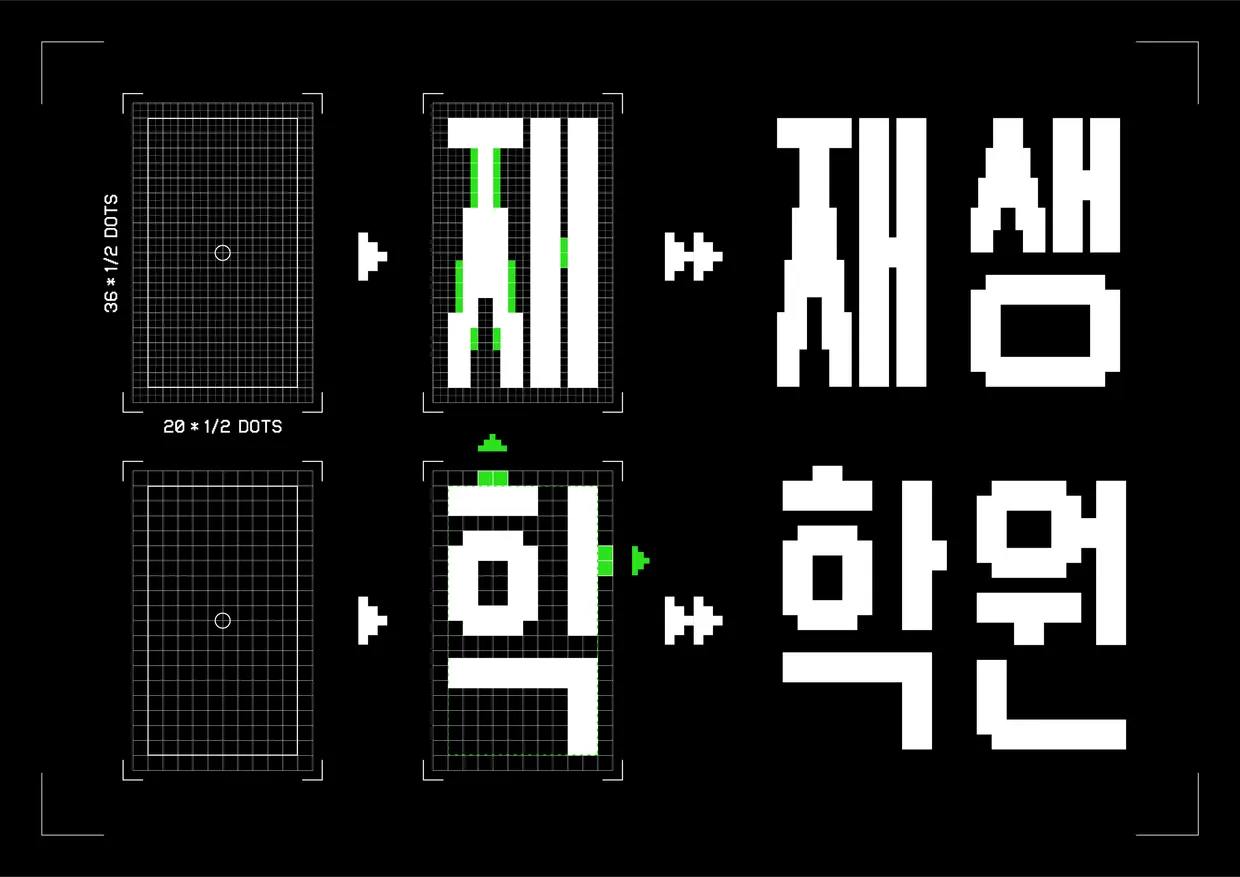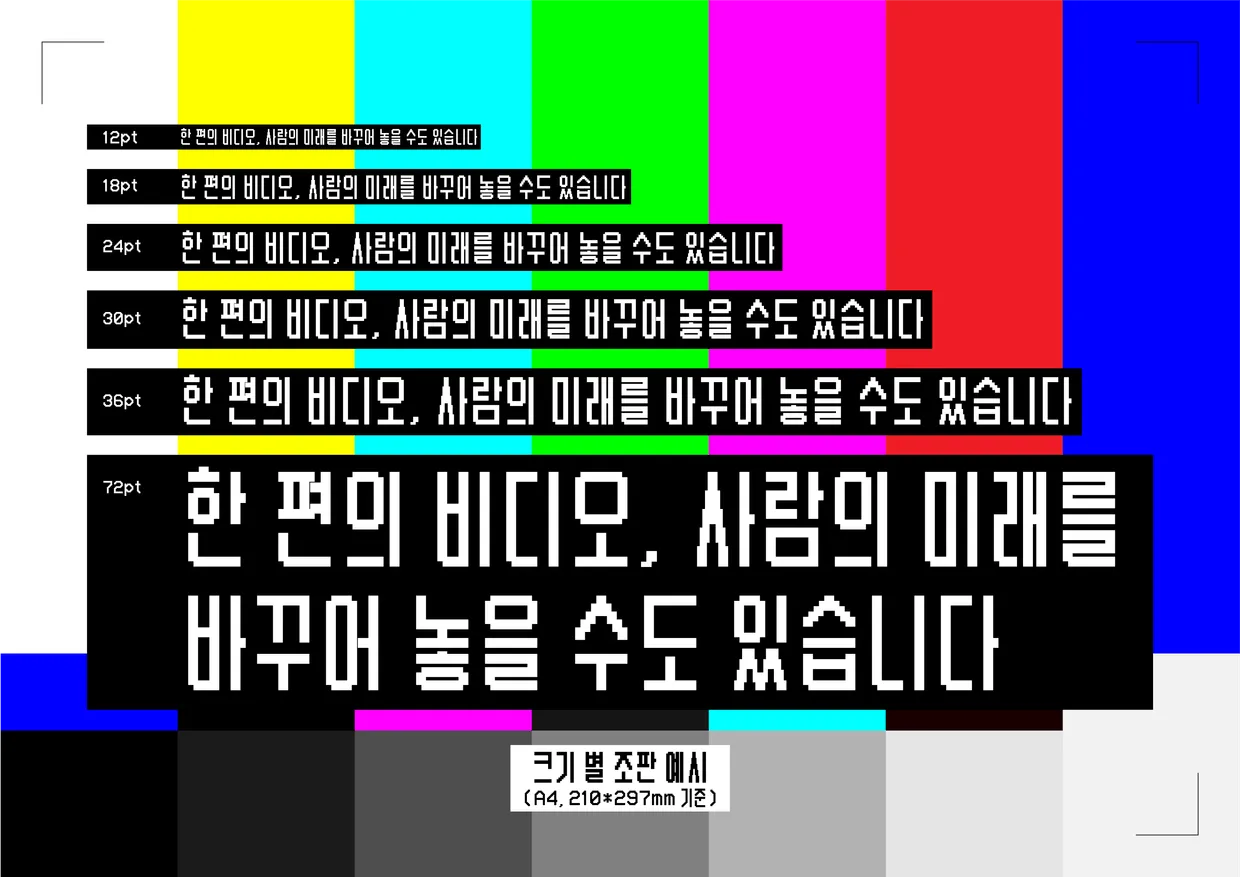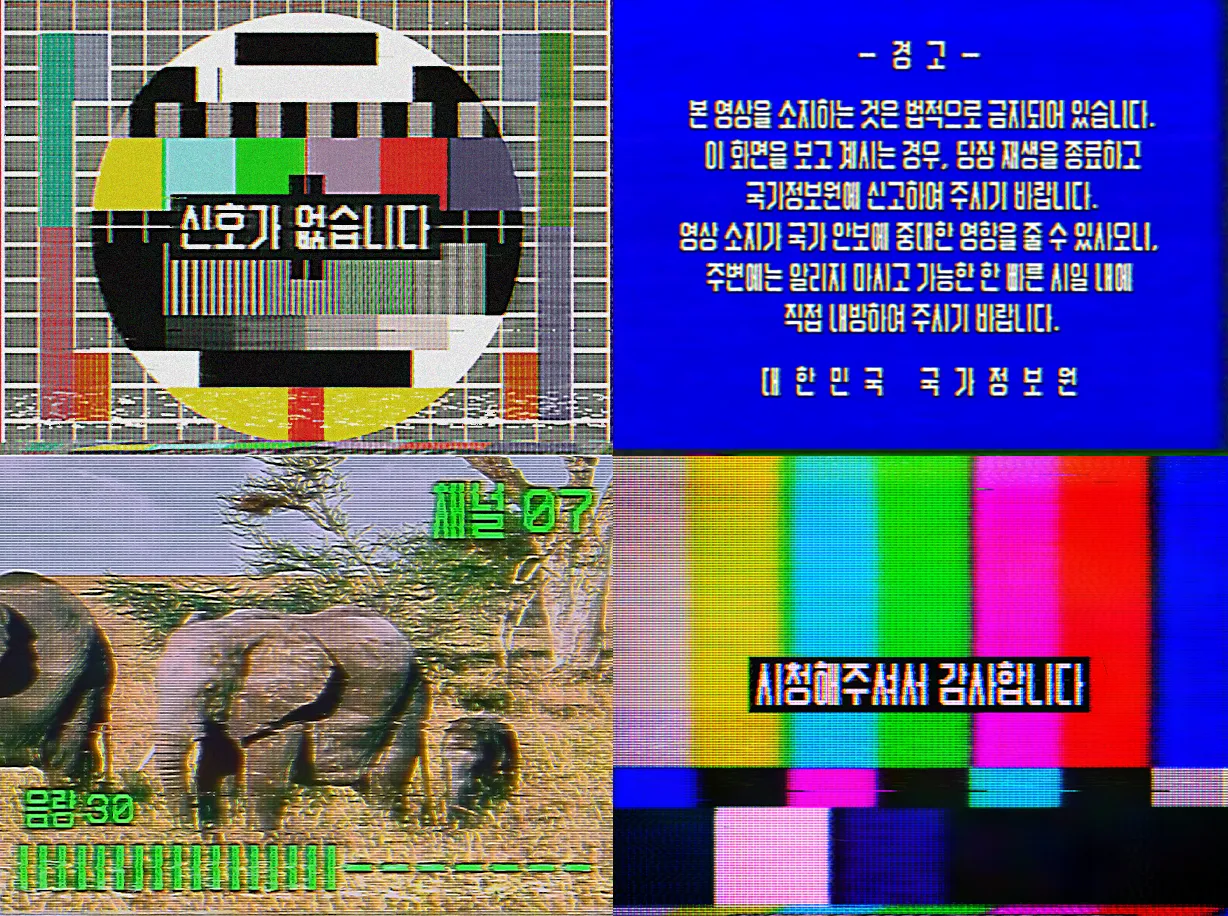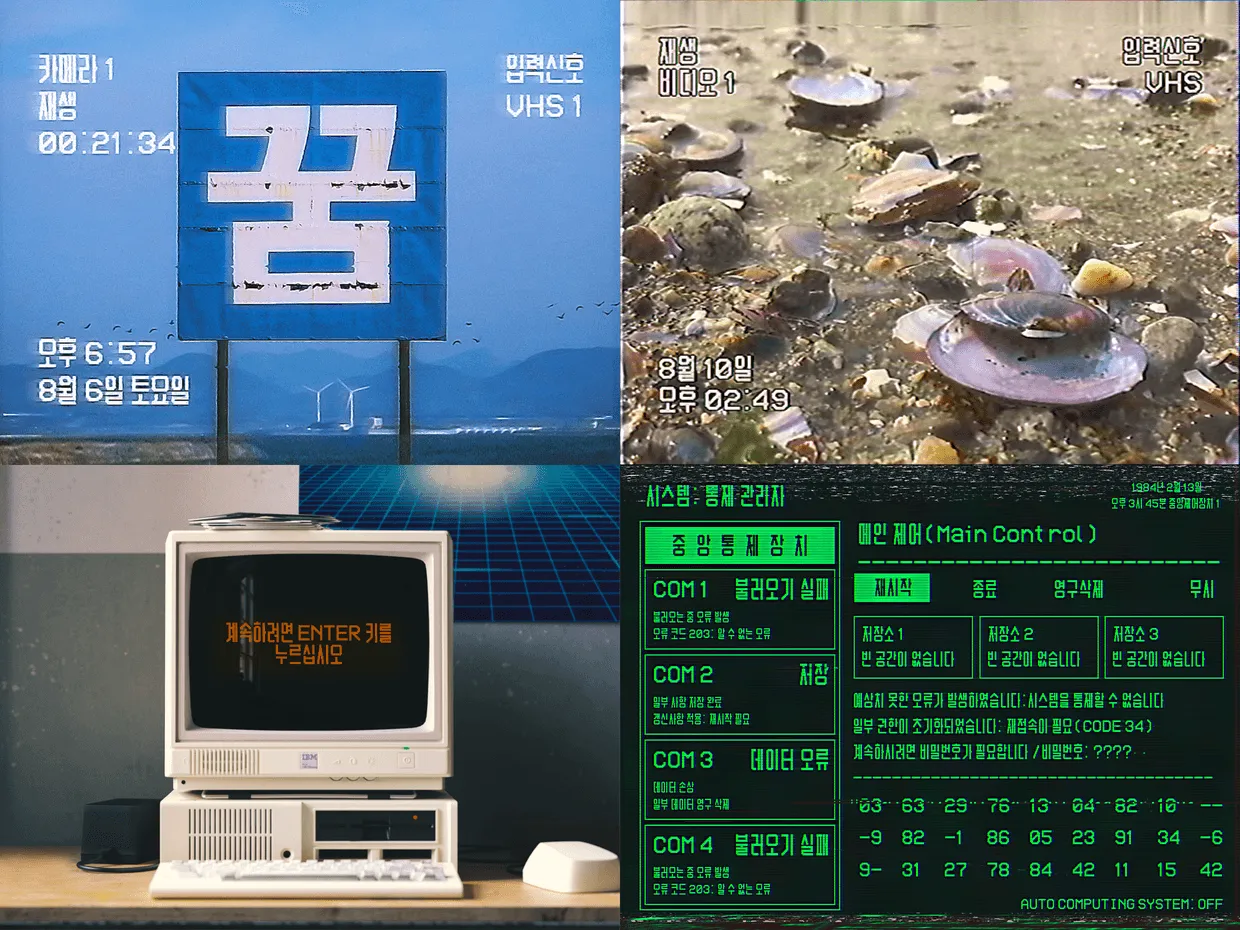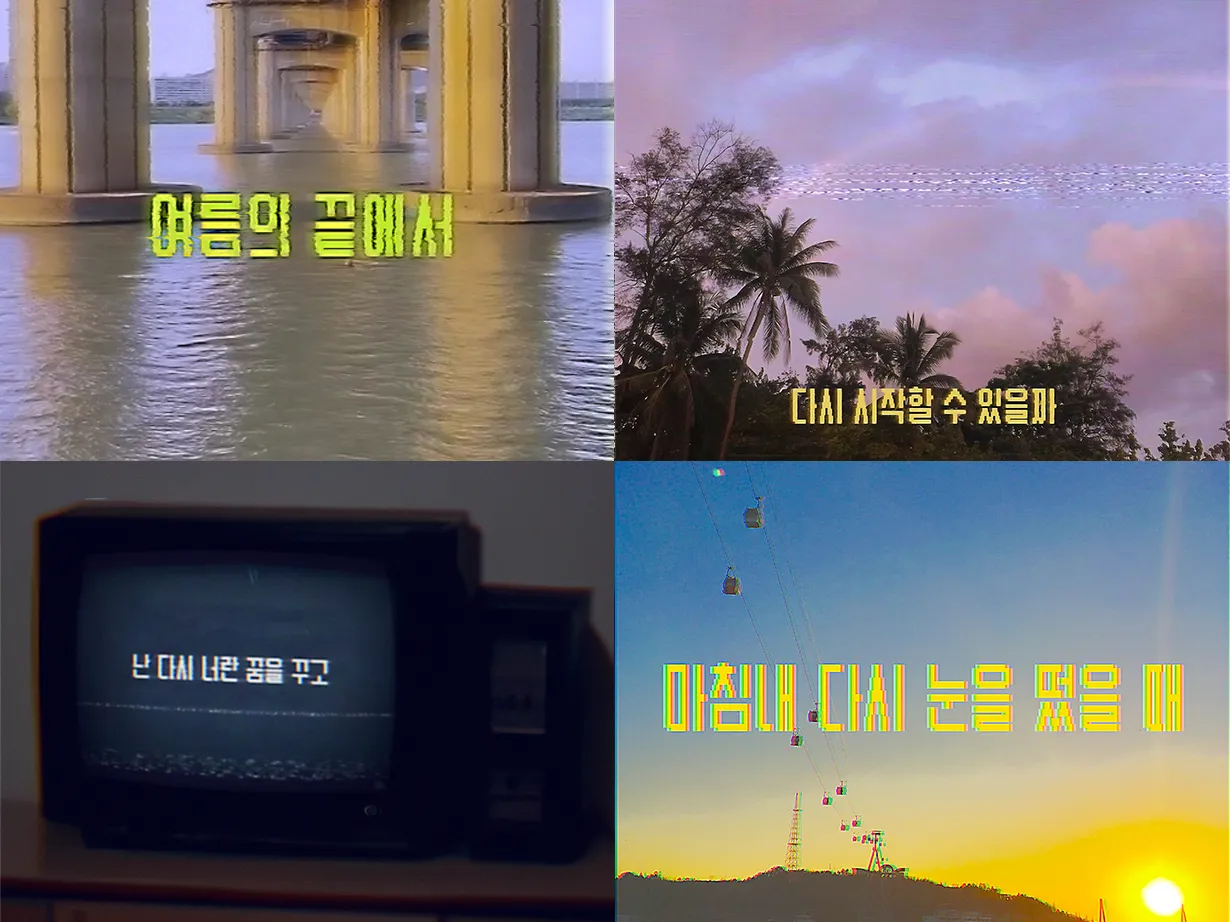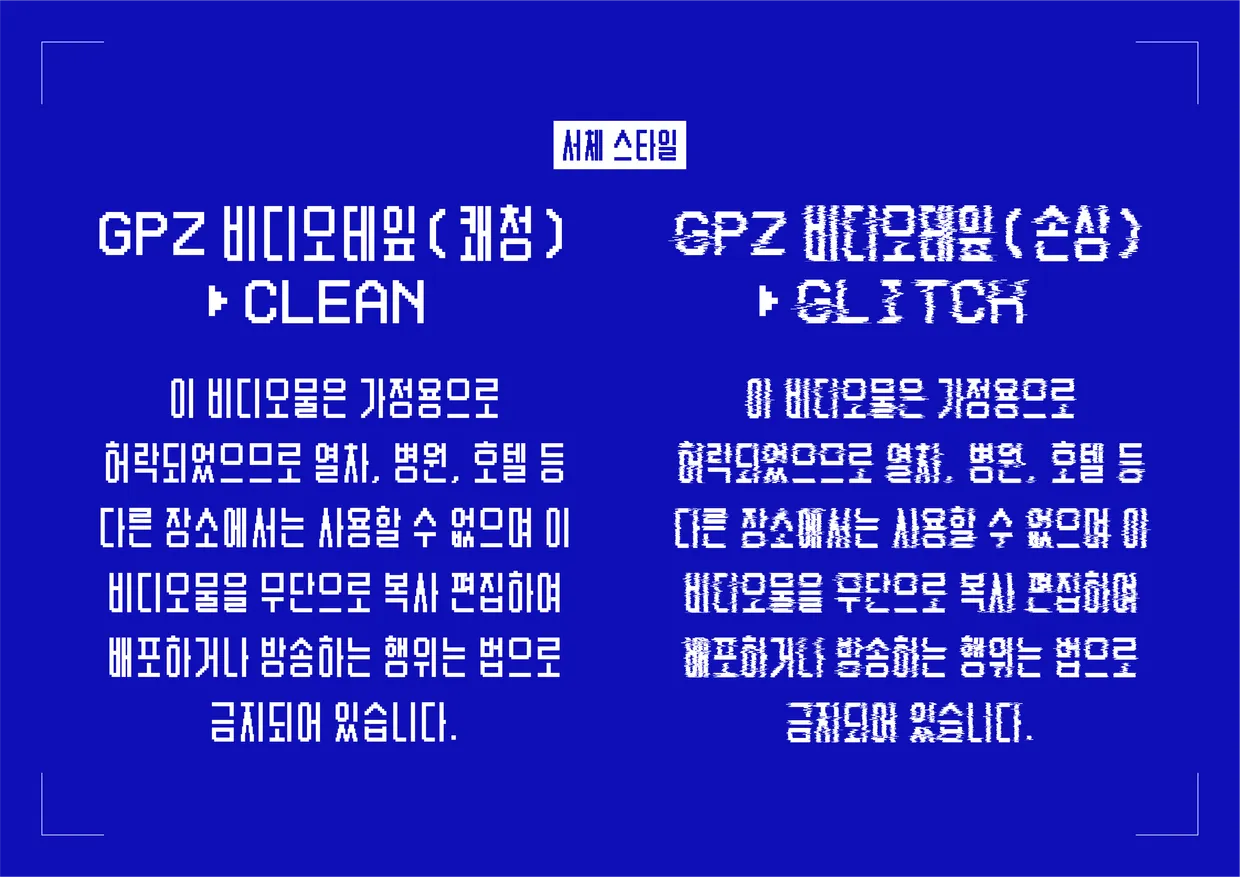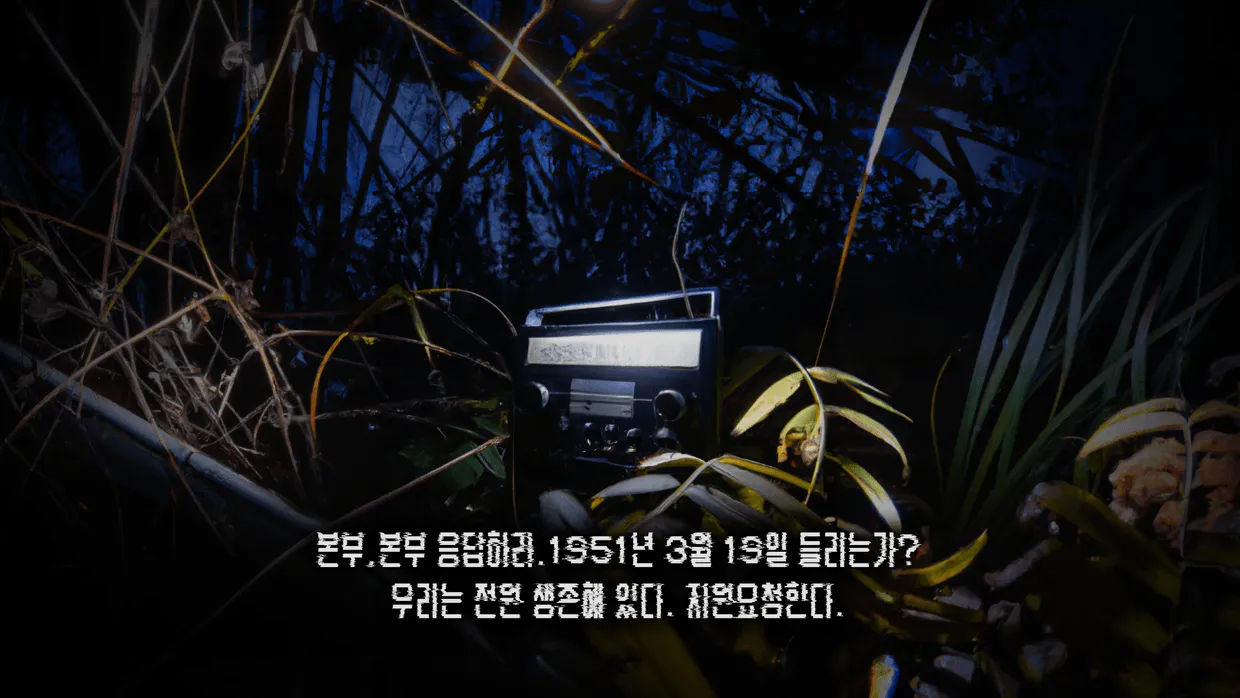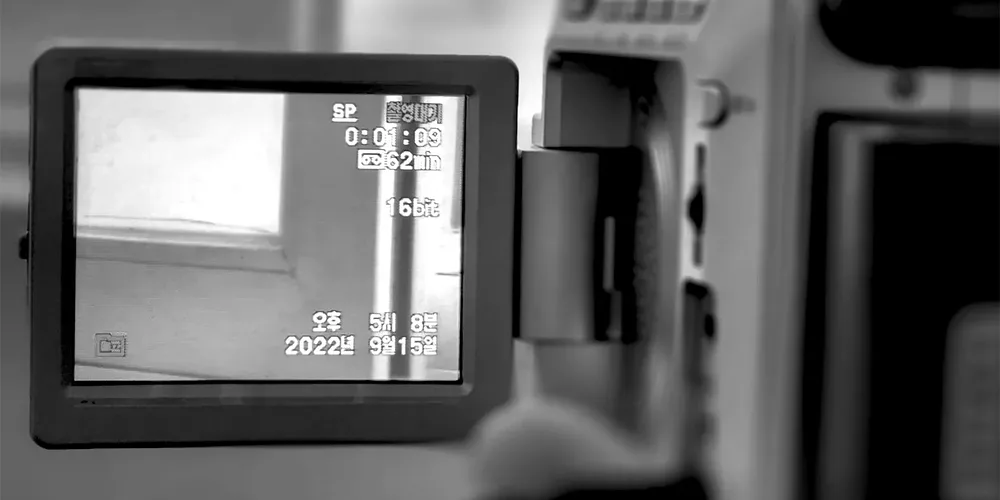
GPZ비디오테잎 소개
'GPZ비디오테잎'은 옛날 비디오 장치를 모티프로 비트맵 형식을 차용한 글꼴입니다. 가로 10 도트, 세로 18 도트의 화질로 그 옛날의 분위기를 재현합니다. 'GPZ비디오테잎'은 기계적인 느낌이나, 오래된 복고의 따뜻한 인상을 재현하고 싶을 때 사용하기 좋은 글꼴입니다.
‘GPZ비디오테잎’은 폭은 좁고, 위아래로 긴 장체의 모습을 띠고 있습니다. 화소가 많지 않던 옛날 TV나 캠코더 속 그 글자처럼, 가로 10개, 세로 18개의 적은 도트로 낱자를 표현합니다. 이렇게 나누어진 도트를 따라 한 획은 두 도트, 자소 간격도 두 도트로 글자를 표현합니다. 한 도트가 표시하는 글자의 최소 단위, 마치 '픽셀'인 셈입니다.
'GPZ비디오테잎'은 도트로 선을 그리다 보니 수직, 수평이 아닌 선을 그릴 때 어려움이 있습니다. 선이 울퉁불퉁해 보이거나 글자의 판독이 어려워지기도 합니다. 그래서 이번 프로젝트에서는 일부를 반 도트로 표현했습니다. 이렇게 반 도트를 사용하면 좁은 공간이 있을 때나 낱자에 사선이 있을 때 보다 자연스럽게 보입니다.
또한 공간 바깥으로 뻗어나가는 줄기(ㅎ, ㅏ 등)가 있는 자소는 기본 공간을 치고 나가도록 설계했습니다. 복잡한 표현이 가능한 보통 활자라면 자소를 안쪽으로 조금 들여서 공간을 보정하지만, 'GPZ비디오테잎'의 경우 표현할 수 있는 도트 수가 적어 오히려 폭이 들쭉날쭉해 보일 수 있습니다. 따라서 기본 공간 바깥으로 뻗어나가도록 했습니다.
‘GPZ 비디오테잎’에는 두 가지 스타일이 있습니다. 일반적으로 사용할 때에 적합한 '쾌청’과 마치 테이프가 손상된 것처럼 군데군데 불량(?) 화소가 보이는 '손상'입니다. 옛날 비디오보다 더 오래된 느낌을 내고 싶을 때, 어쩐지 으스스한 공포 분위기를 연출하고 싶을 때에는 '손상'을 활용해 보시는 건 어떨까요?